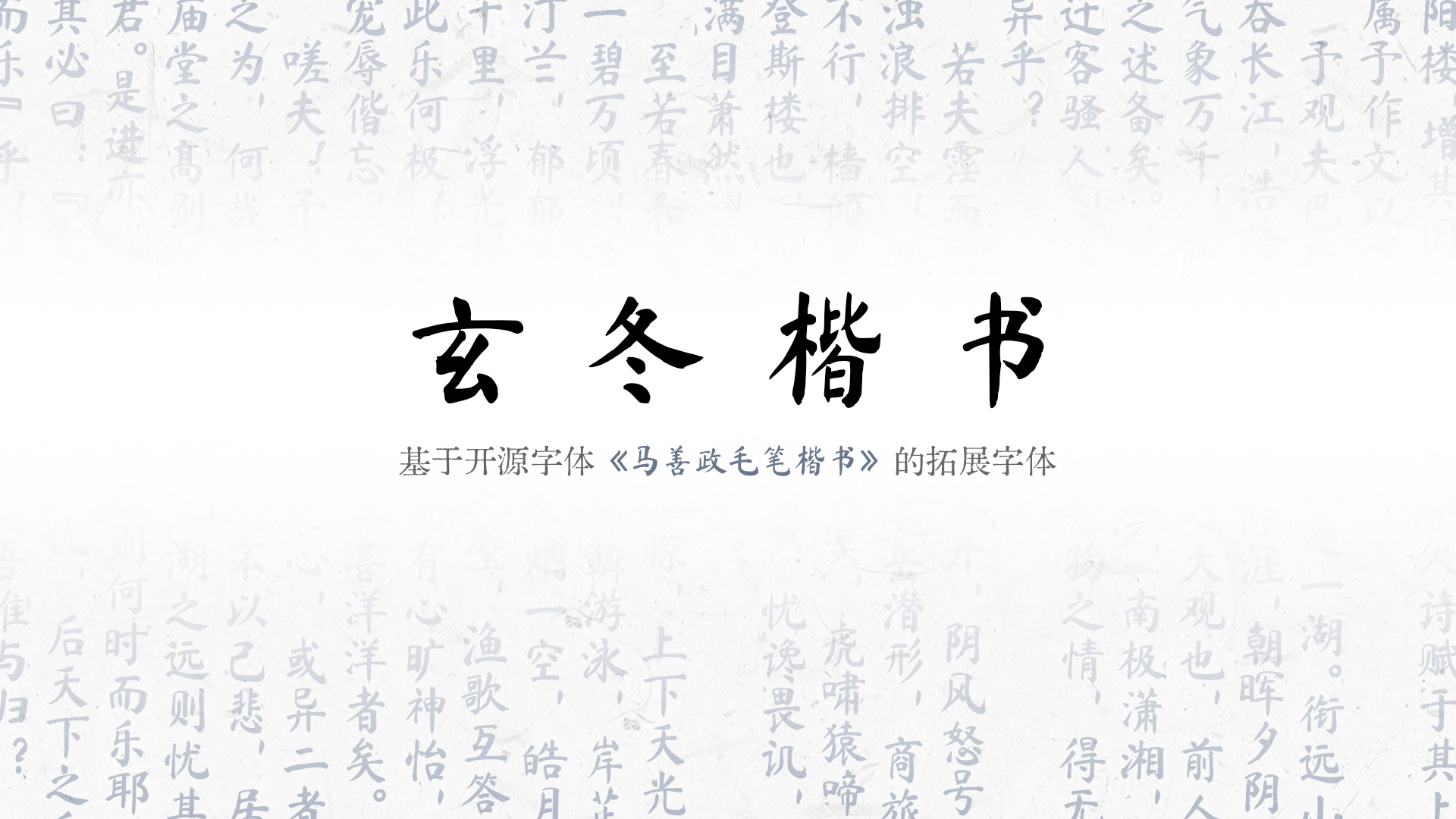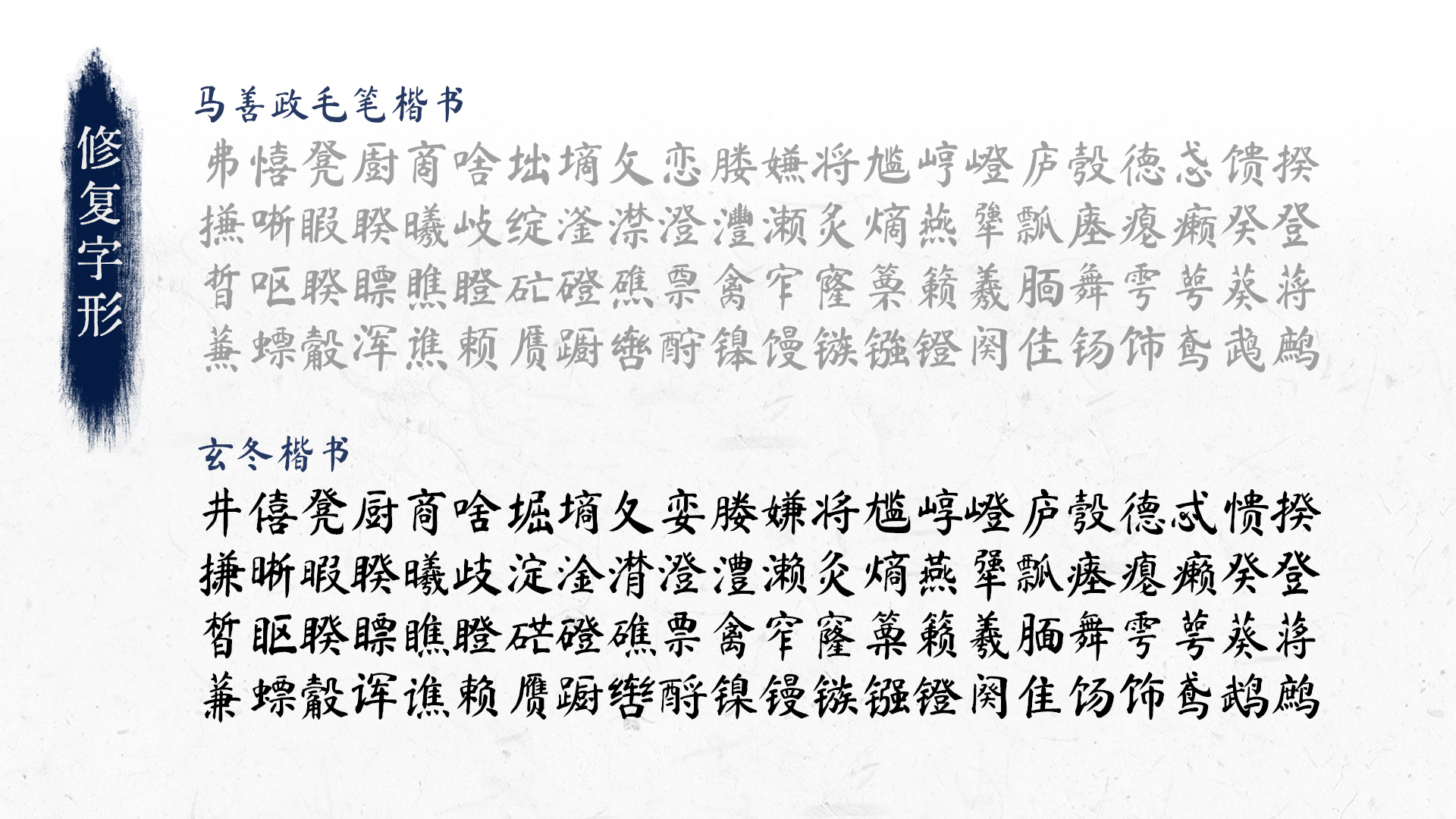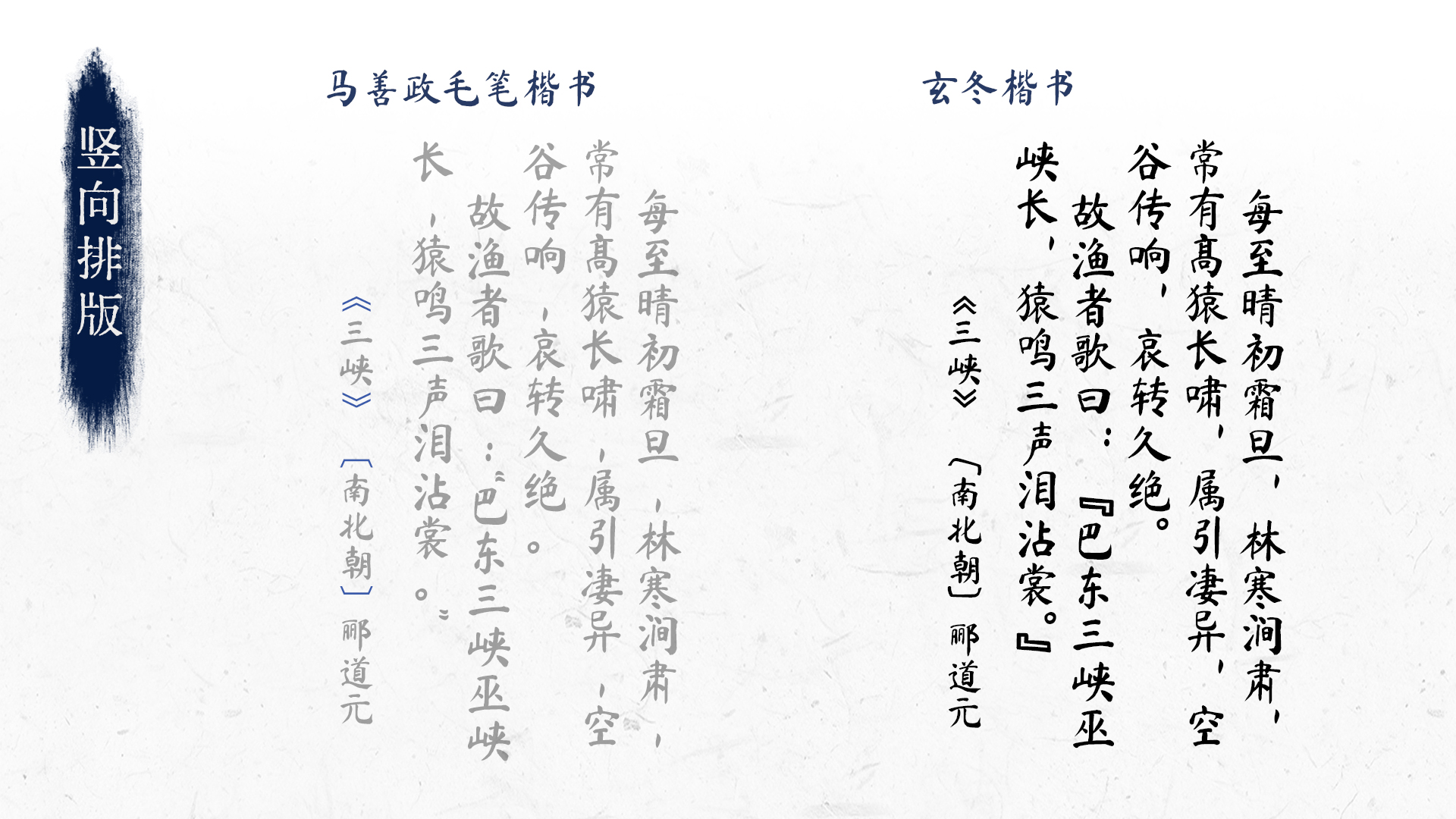
玄冬楷书(Xuandong Kaishu)是设计师 Skr-ZERO 基于谷歌开源字体马善政毛笔楷书进行拓展与修复形成的一款新的免费可商用楷书字体。
字体修复了原版中存在的一些错误字形,使字体更加规范。同时增添了竖排排版,特别适配古籍复刻、中式竖排海报等排版需求。
修改内容
- 修复以下88字:
井僖凳厨商啥堀墒夂娈媵嫌将尴崞嶝庐彀德忒愦揆
搛晰暇睽曦歧淀淦潸澄澧濑灸熵燕犟瓢瘗瘪癞癸登
皙眍睽瞟瞧瞪硭磴礁票禽窄窿篥籁羲腼舞雩萼葵蒋
蒹螵觳诨谯赖赝蹰辔酹镍镘镞镪镫阕隹饧饰鸢鹉鹧
- 调整都分汉字字面的问题。
- 增加
vert 特性,用于竖向排版。
- 新增“啰瞭”二字,补全一级通用规范字。